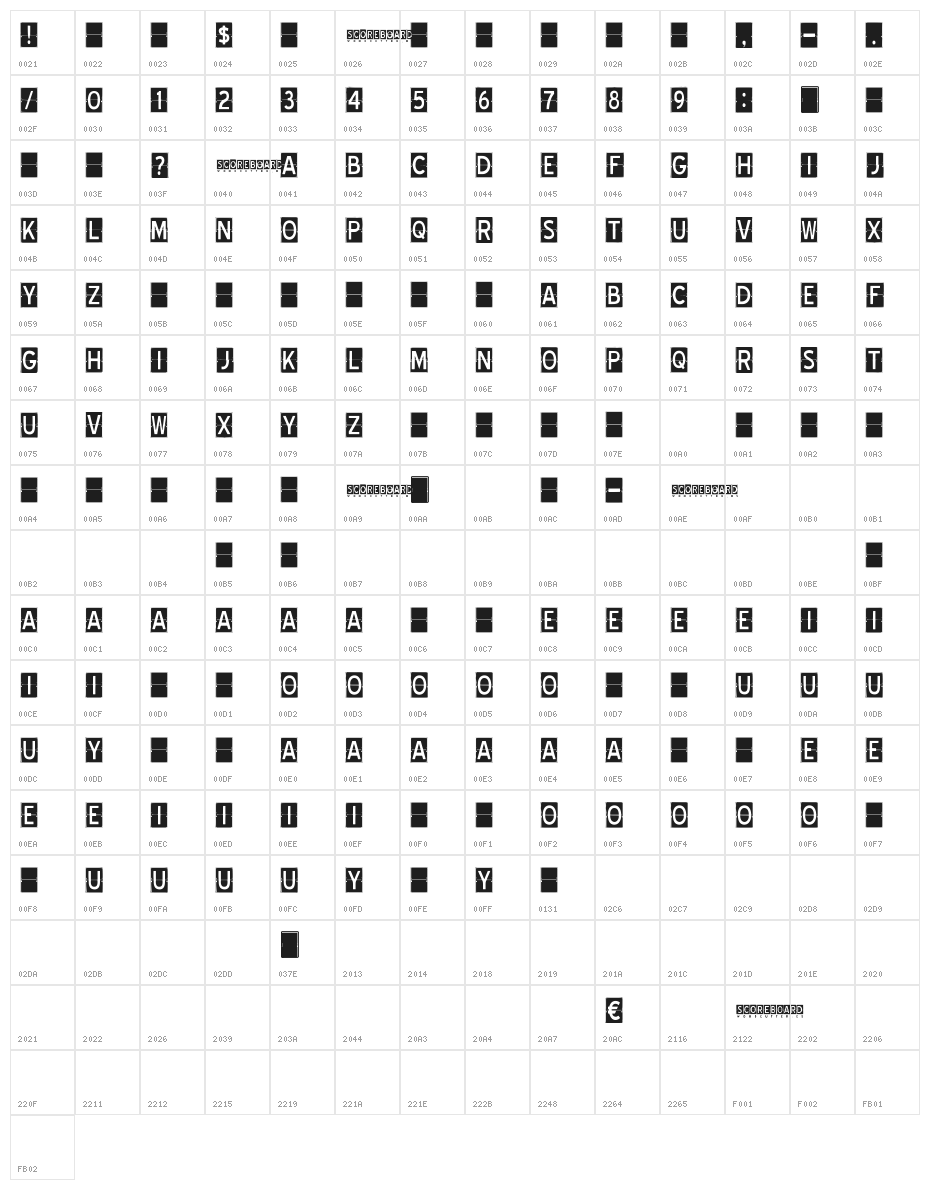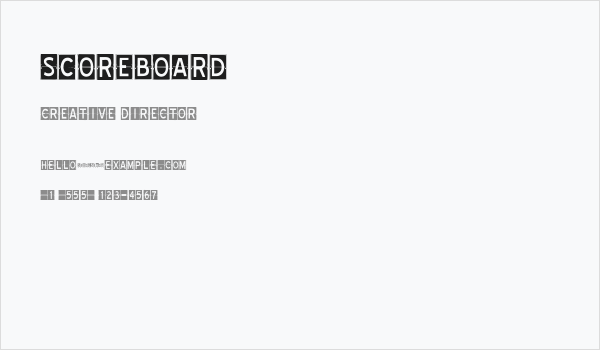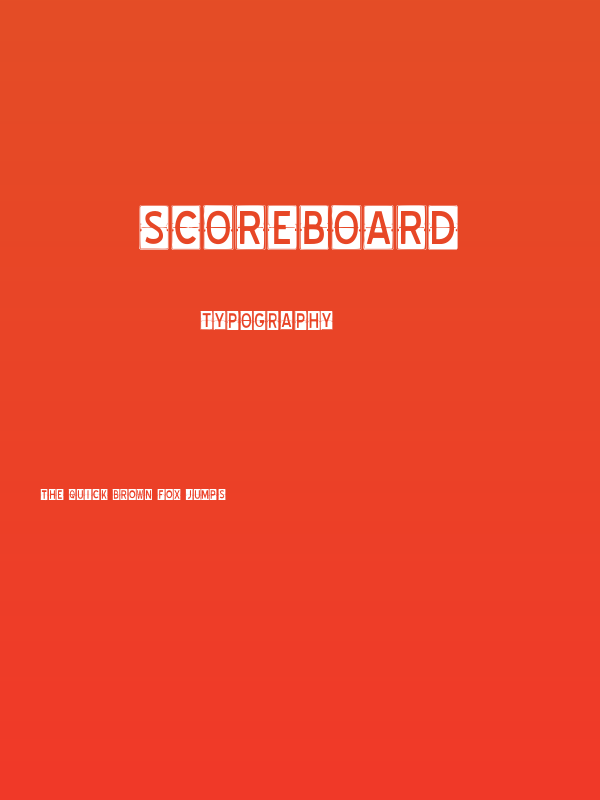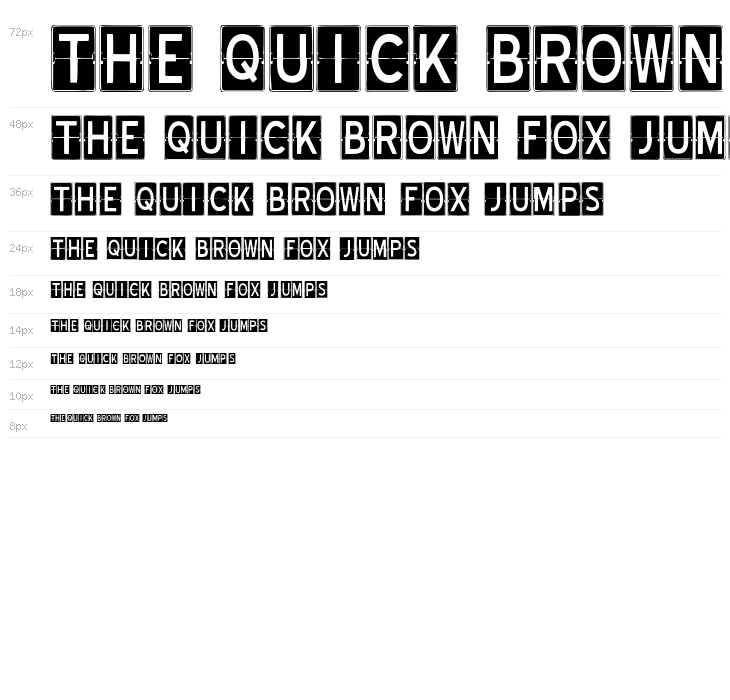
SCOREBOARD Font
| حالة الاستخدام | Headlines, Logos, Digital Displays |
| مشاريع مقترحة | Ideal for sports-related designs, digital displays, retro-themed projects, and any application requiring a bold, attention-grabbing typeface. |